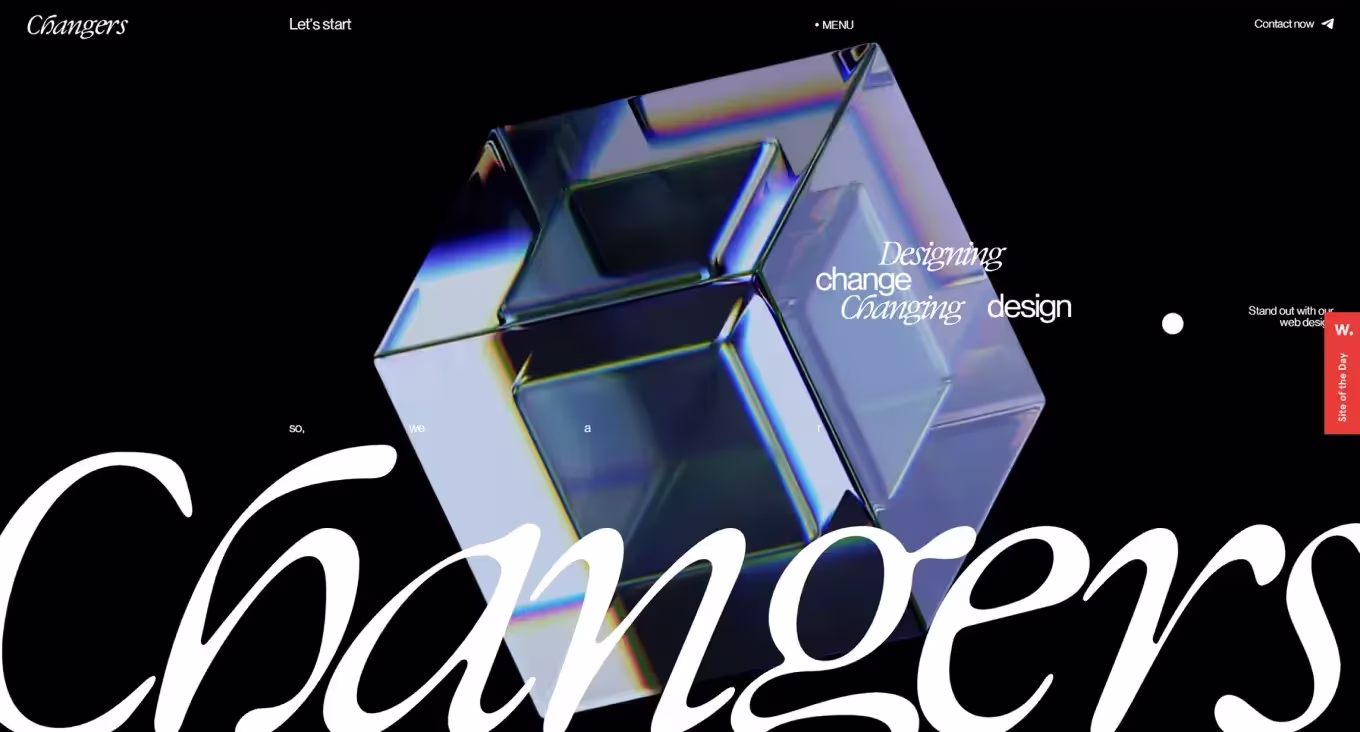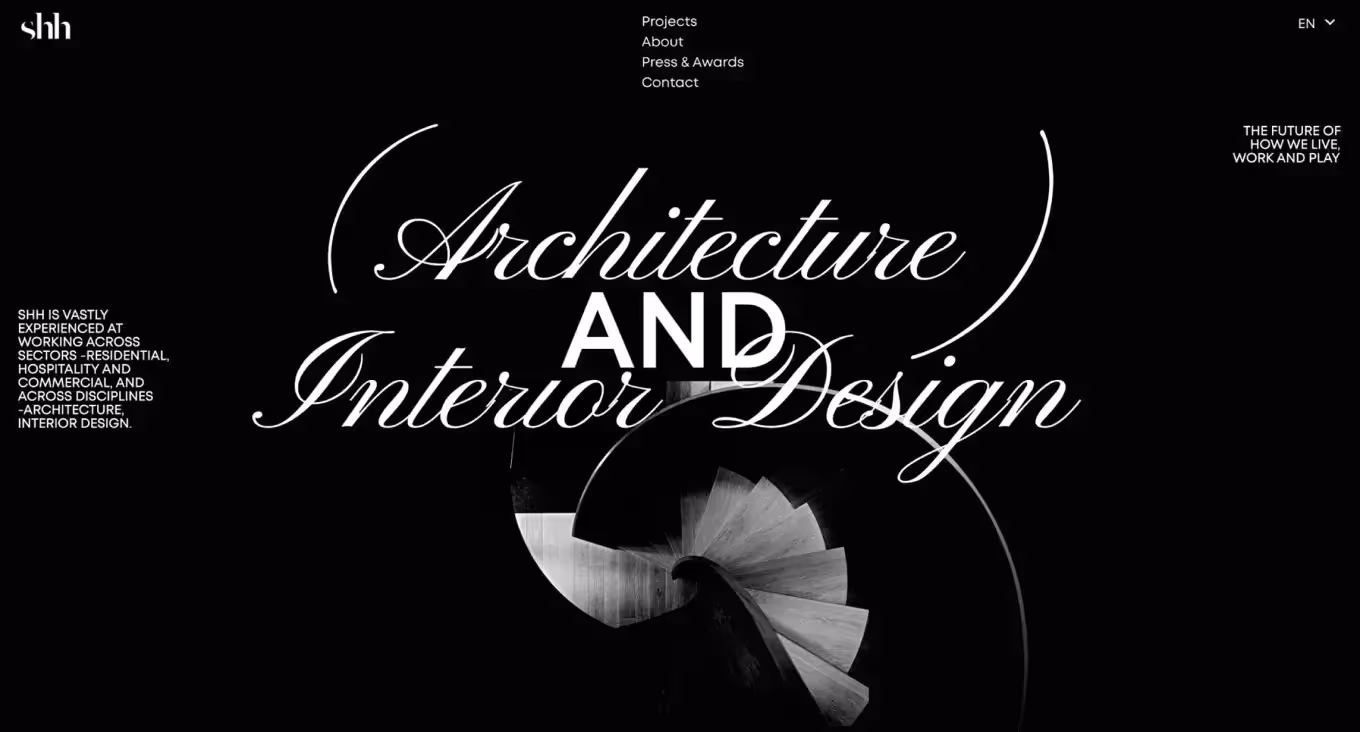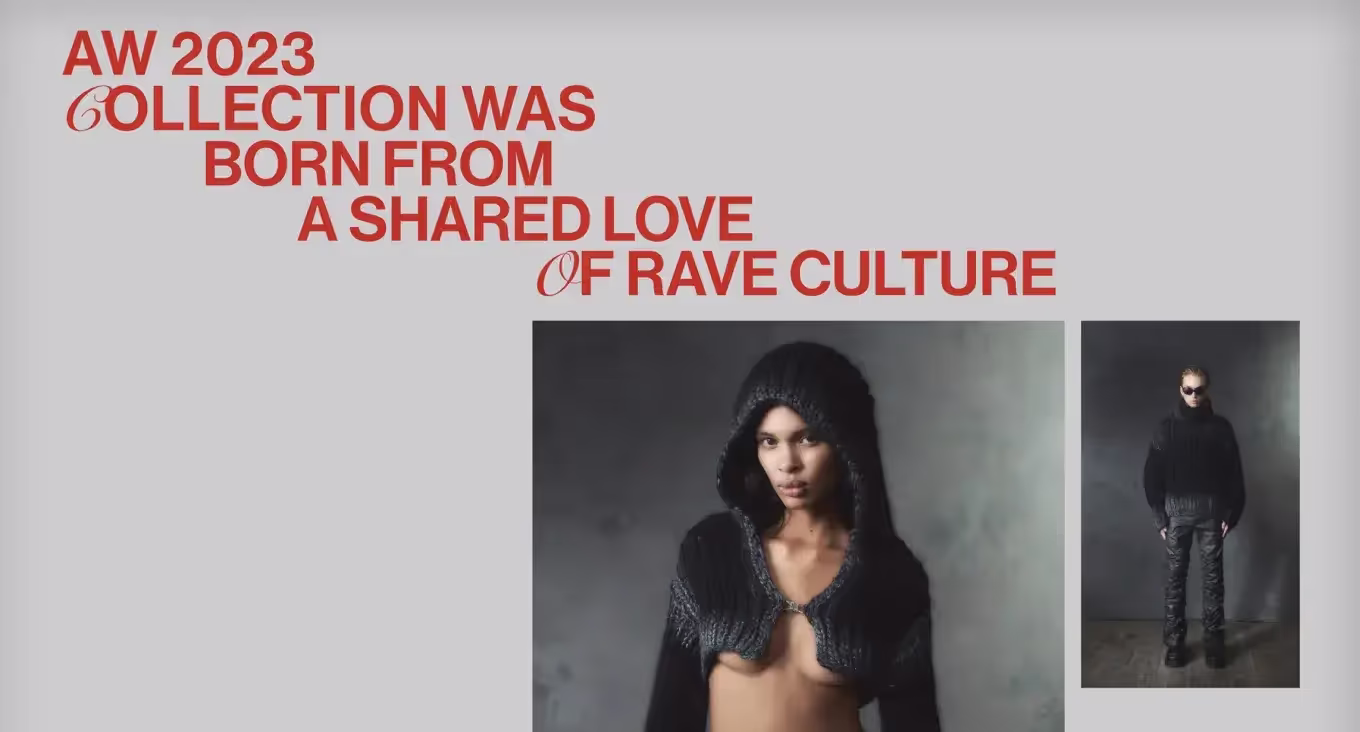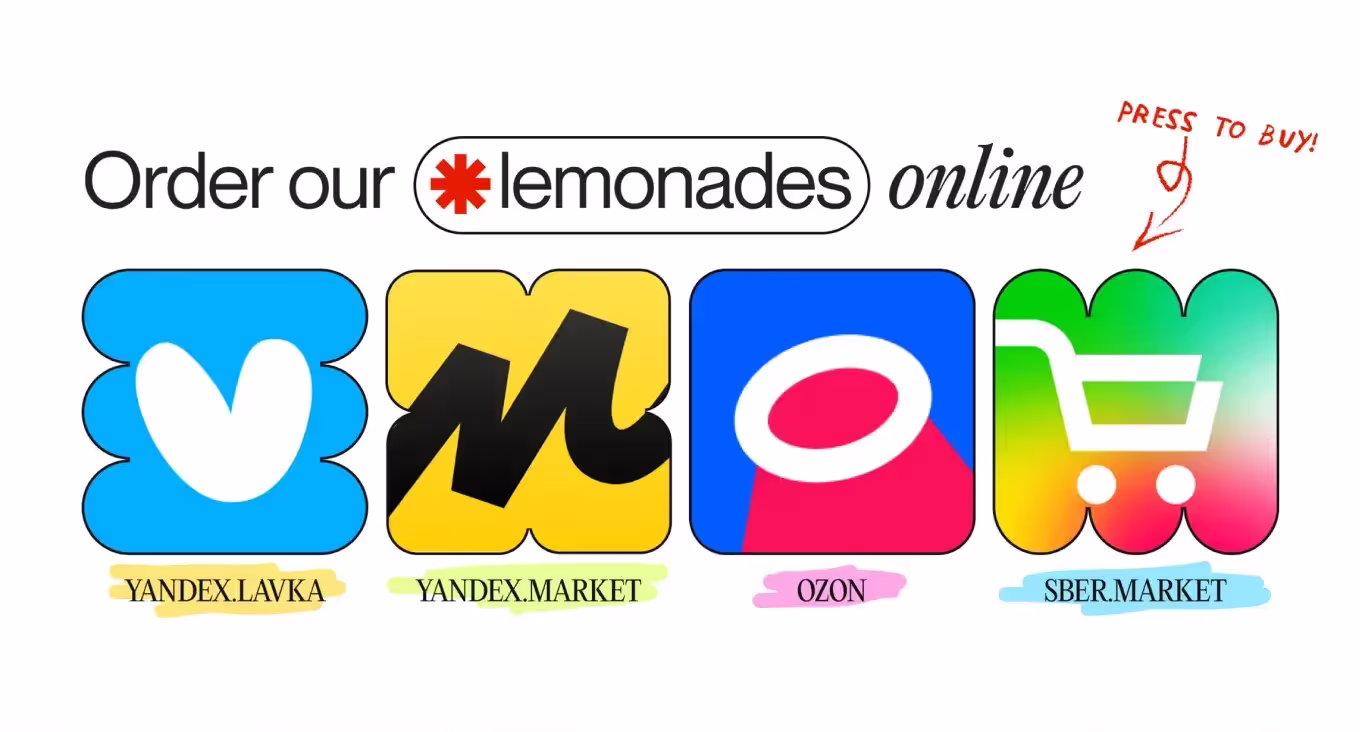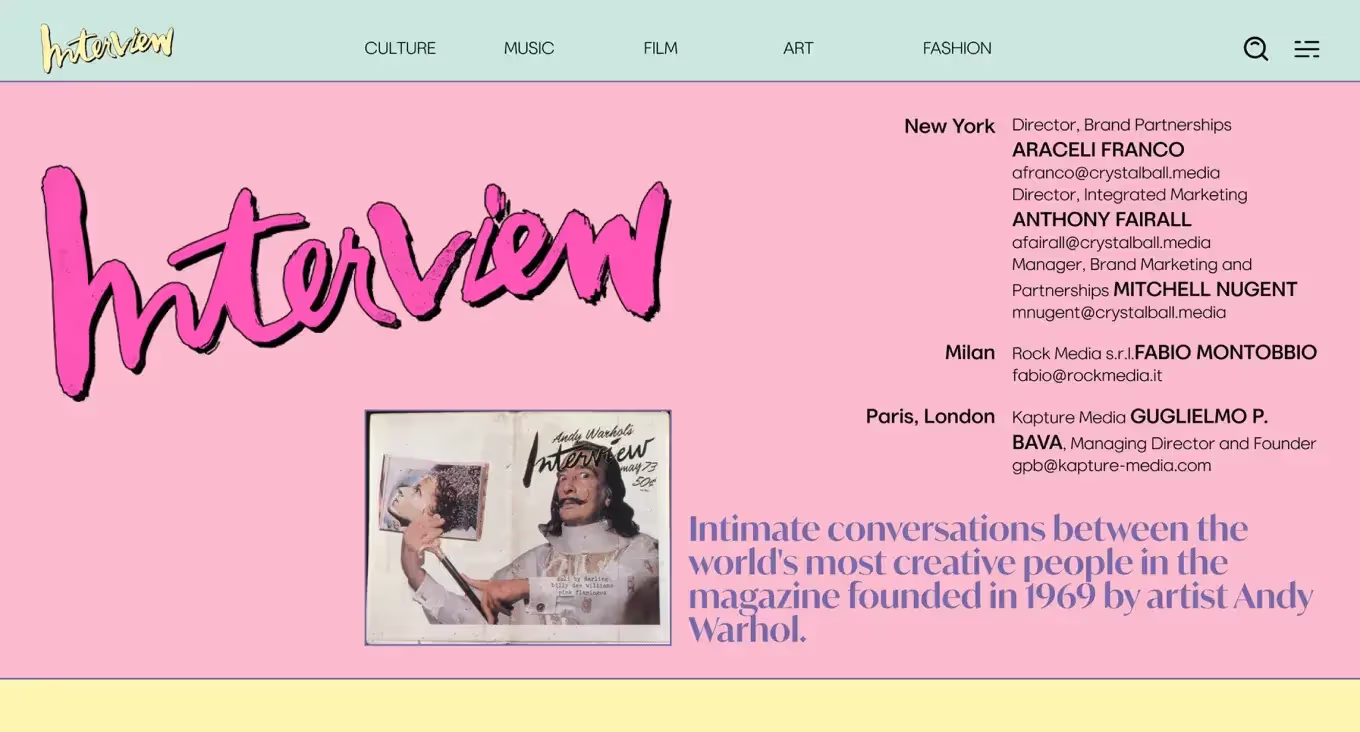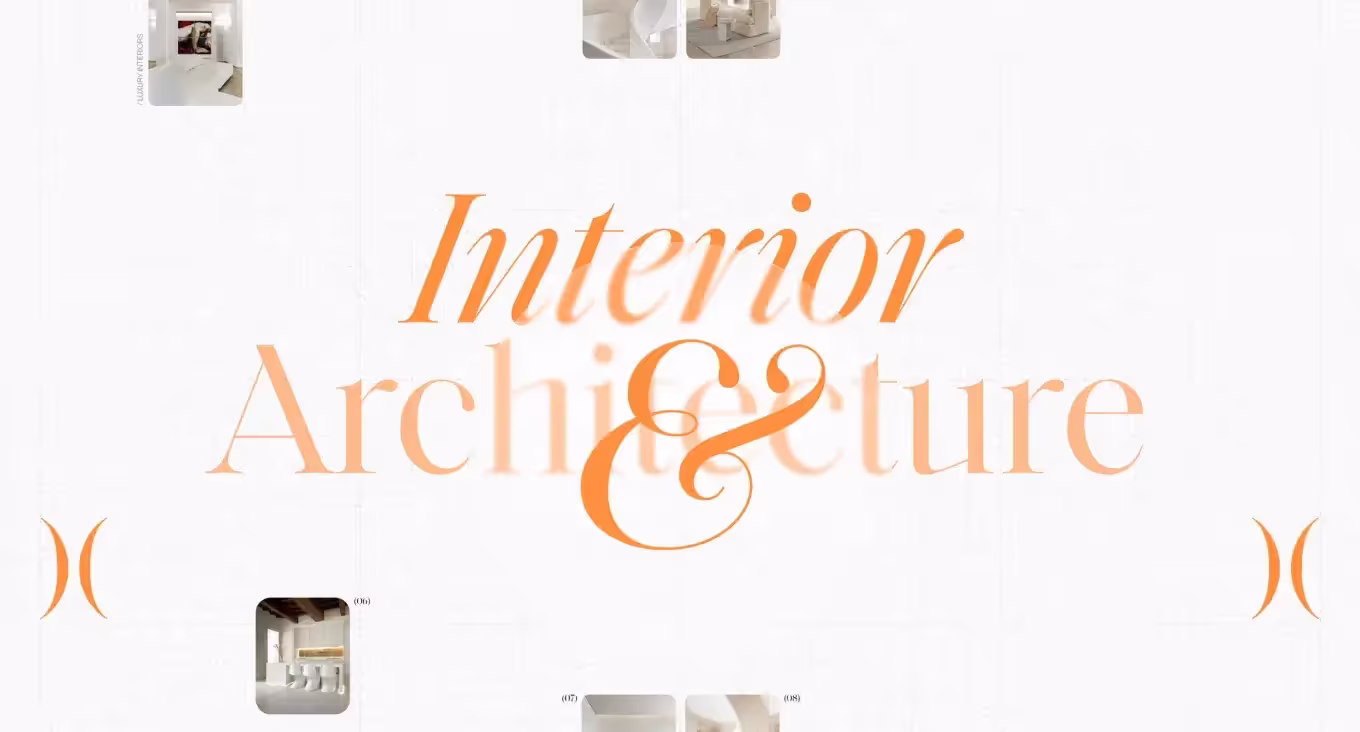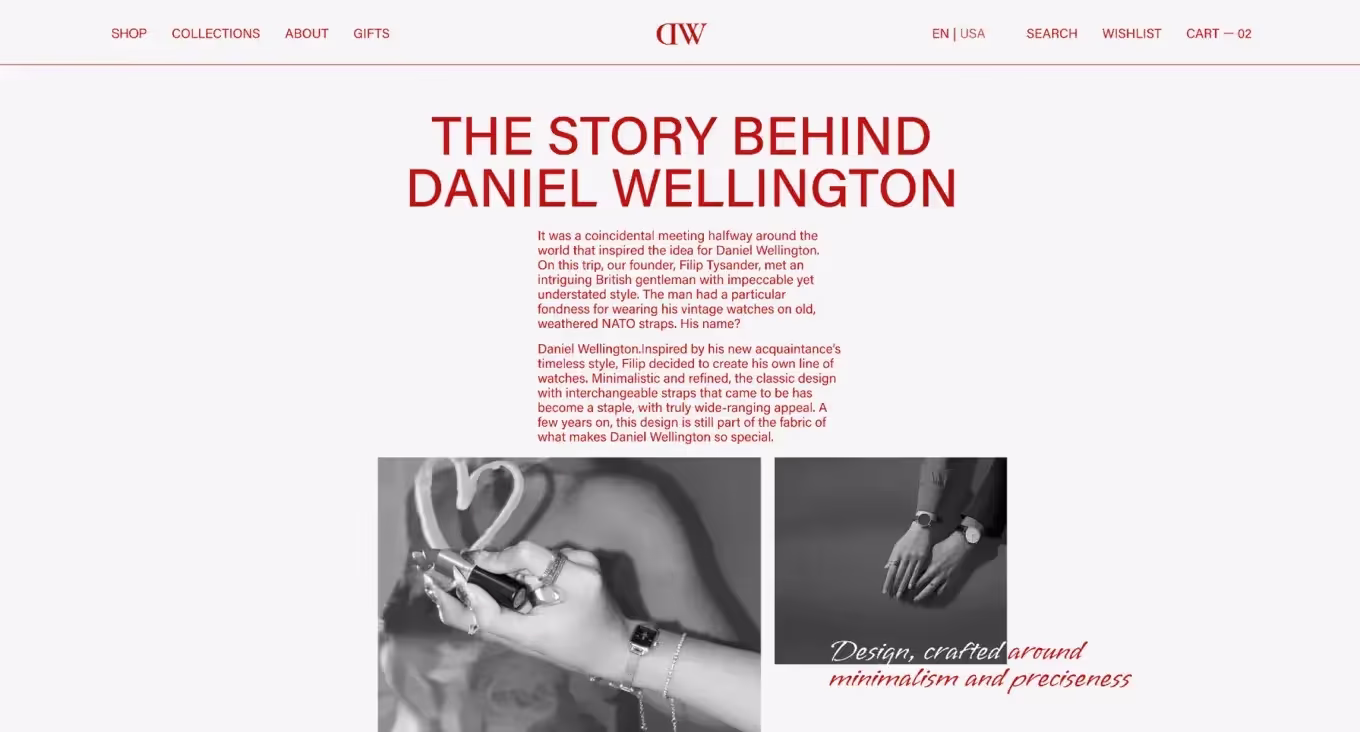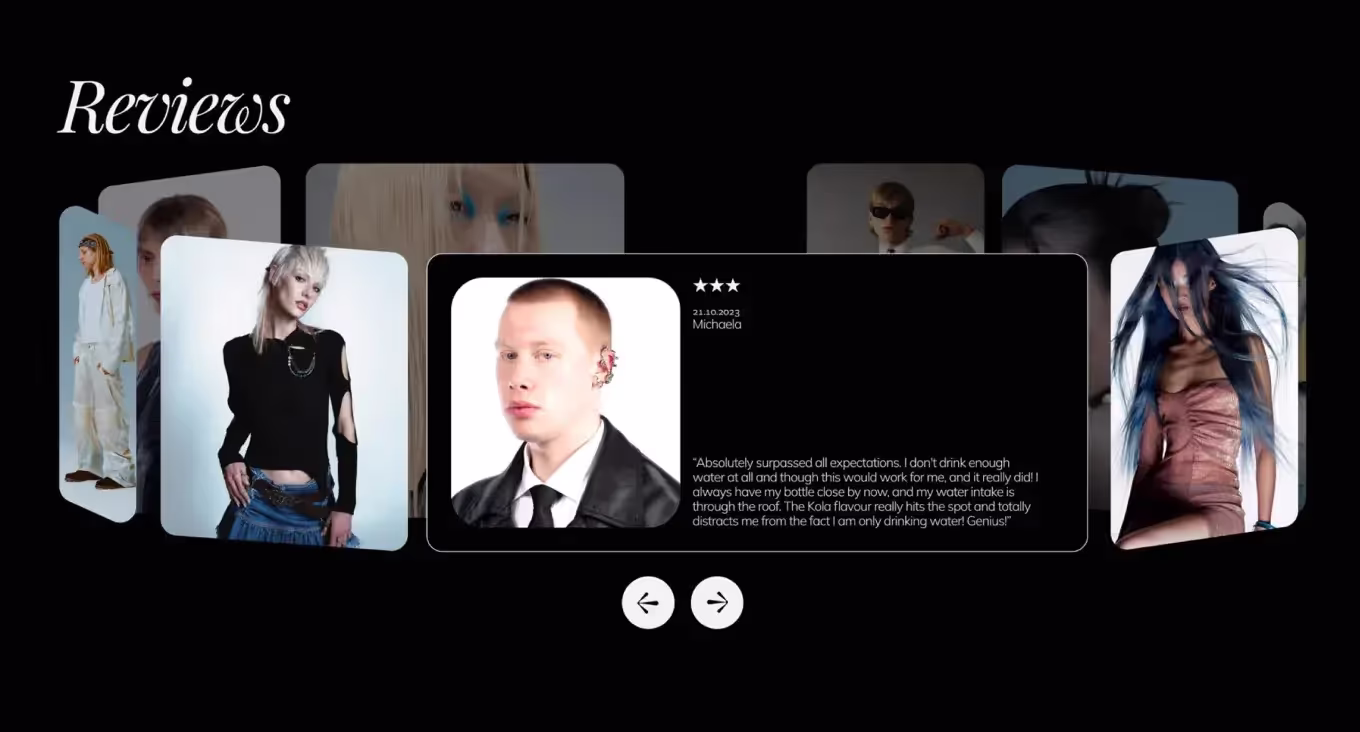
Рукописные шрифты в дизайне
Введение
Рукописные тексты смотрятся непривычно в сфере цифрового дизайна. Тем самым они освежают интерфейсы и привлекают внимание пользователей. Но при работе с рукописным текстом дизайнер должен соблюдать баланс между эстетикой и функциональностью, креативностью и читабельностью.
В этой статье мы расскажем об использовании рукописных шрифтов в UX/UI-дизайне. Мы обсудим их преимущества и недостатки, восприятие с психологической точки зрения, а также лучшие практики для создания ваших макетов и вдохновляющие примеры. Кроме того, мы поделимся полезными ресурсами для тренировки насмотренности и подбора шрифтов.
Что такое рукописный текст
Под «рукописным» подразумевается текст, напечатанный шрифтом, который имитирует настоящий рукописный почерк. Это создает впечатление, что текст написан от руки. Такой прием делает дизайн более оригинальным и индивидуальным. Чаще всего их используют для оформления заголовков, цитат и расставления акцентов.
Мы знаем, что стандартные шрифты отлично подходят для строгих, серьезных и функциональных товаров. Что касается рукописных шрифтов, они хорошо работают для оформления интерфейсов, связанных с едой, модой, впечатлениями, товарами для ухода за собой и т. д. Поскольку они вызывают больший эмоциональный отклик и привязанность.
Преимущества рукописных шрифтов
Если суммировать преимущества использования рукописных шрифтов, то к ним относятся:
1. Уникальность и индивидуальность
Использование рукописных шрифтов дает возможность выделиться и привлечь внимание аудитории. Ведь каждый почерк уникален, поэтому рукописные шрифты ассоциируются с отдельной личностью.
2. Передача настроения и эмоций, повышение экспрессивности
Рукописные шрифты хорошо передают эмоции. Они также могут создавать атмосферу, нужную для конкретного продукта или сайта.
3. Усиление брендинга и идентичности
При создании логотипов, упаковок и других элементов брендинга рукописный шрифт помогает создать запоминающийся дизайн. Это касается и создания интерфейсов.
4. Добавление креативности и эстетичности
Рукописные шрифты могут разнообразить типографику вашего интерфейса, привнести яркие акценты и контрасты.
5. Повышение узнаваемости
Если вы сможете создать ассоциацию между брендом и шрифтом, пользователи будут вспоминать и узнавать ваш бренд быстрее.
В то же время нужно иметь в виду некоторые недостатки рукописных шрифтов:
01
Выбор рукописных шрифтов не такой большой в сравнении с обычными шрифтами. Кроме того, больше всего вариантов созданы для латиницы.
02
Если уделить все внимание эстетической стороне создания текста, можно сильно снизить его читабельность. Также некоторые рукописные шрифты сами по себе слишком сложны для восприятия.
03
Рукописный шрифт нужно подбирать четко под определенную тематику сайта или приложения. Иначе вы создадите диссонанс и запутаете или даже оттолкнете пользователя.
Психология восприятия рукописных шрифтов
Если вы знаете, как работает человеческое восприятие, вы сможете вызвать нужную реакцию у пользователей с помощью различных шрифтов. Поэтому давайте немного поговорим про ассоциации.
Рукописные шрифты разнообразны: некоторые можно назвать забавными, милыми, непринужденными, а другие — традиционными и старомодными. Поэтому при выборе вида рукописного шрифта учитывайте, к какой категории он относится. Это поможет вам избежать несоответствия между дизайном и содержанием интерфейса.
Также существуют общие представления о том, что выражают те или иные характеристики шрифтов:
01
Плавные линии, скругленные углы, легкость — все это делает шрифт изящным, нежным и женственным.
02
Угловатость, массивность и резкость характерны для брутальных и смелых шрифтов, которые можно использовать, например, для мужской аудитории.
03
Прямые вытянутые линии характерны для делового или нейтрального стиля.
04
Округлые черты и небольшая надутость придают шрифту детскую непосредственность, делают его игривым.
Поэтому при выборе шрифта также думайте о целевой аудитории: ее составе, возрасте, предпочтениях и ожиданиях.
Полезные советы
Далее мы поделимся советами о том, как использовать рукописные шрифты, с чем их можно сочетать, и как обеспечить читаемость таких текстов. Но давайте начнем с общих правил:
1. Не используйте слишком много гарнитур (семейств шрифтов)
Обычно для создания хорошей типографики достаточно использовать две гарнитуры, которые хорошо сочетаются между собой. Для очень минималистичных интерфейсов можно выбрать всего одну гарнитуру и по необходимости менять ее начертания (жирный, курсив и т. д.). В редких случаях допустимо использовать три гарнитуры, но этот вариант не подходит для начинающих дизайнеров.
2. Выбранная гарнитура должна хорошо смотреться в любом размере
Это правило связано с форматом экранов разных устройств. Часть пользователей будут просматривать ваш сайт с компьютеров и ноутбуков, а часть — с мобильных устройств. По этой причине вам придется менять размер шрифтов, при этом надписи всегда должны оставаться разборчивыми и аккуратными.
Итак, рукописные шрифты привлекают и пользователей, и дизайнеров. Их главное преимущество заключается в том, что они хорошо передают эмоции, настроение и создают нужную атмосферу.
Главное при работе с рукописными шрифтами — подобрать вариант, который подойдет для вашей аудитории и тематики сайта или приложения.
Кроме того, важно убедиться в том, что такой шрифт не затрудняет чтение контента. Для этого учитывайте контрастность фона и шрифта, размер и начертания символов, а также общую структуру и организацию текста.